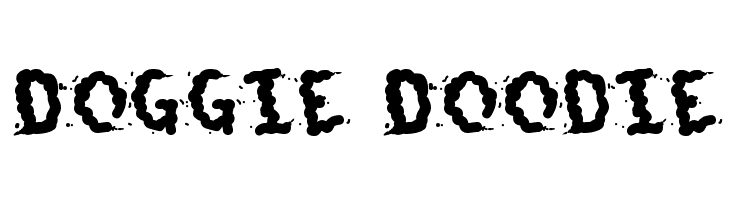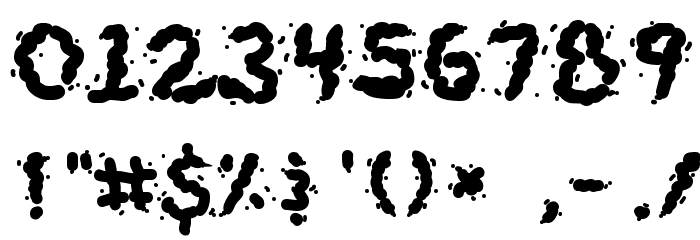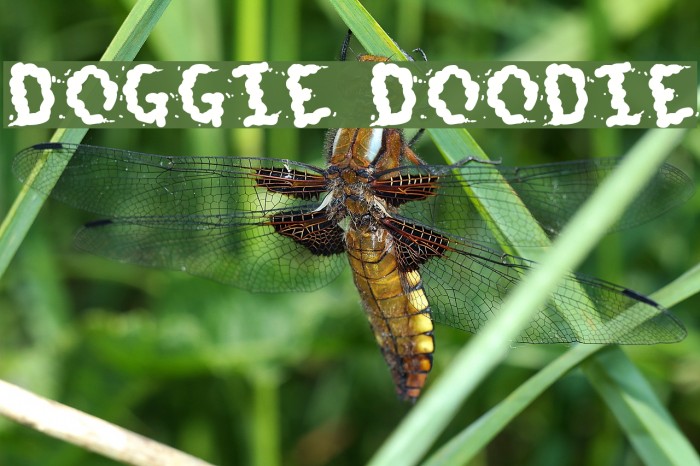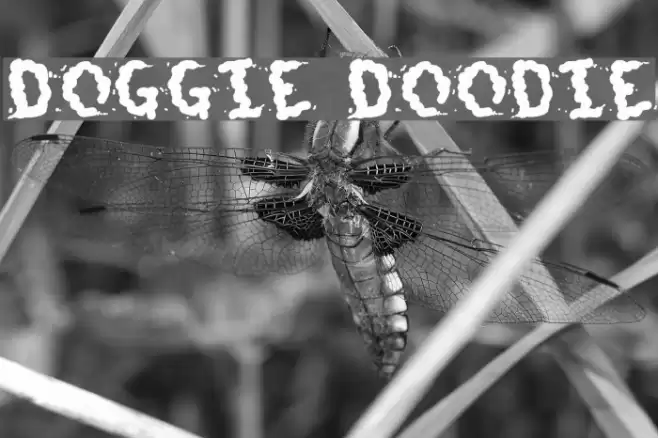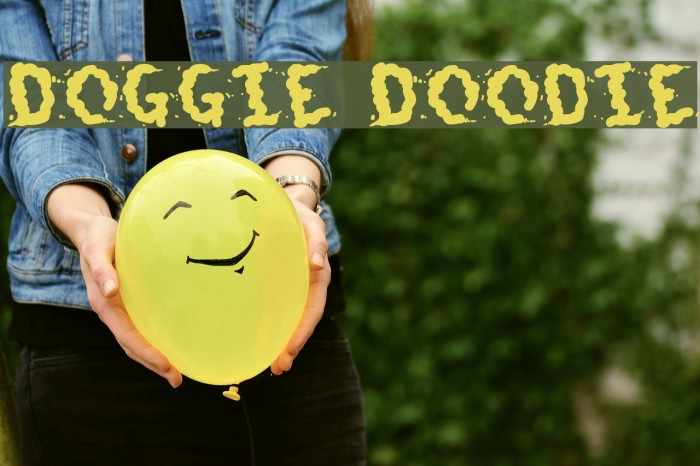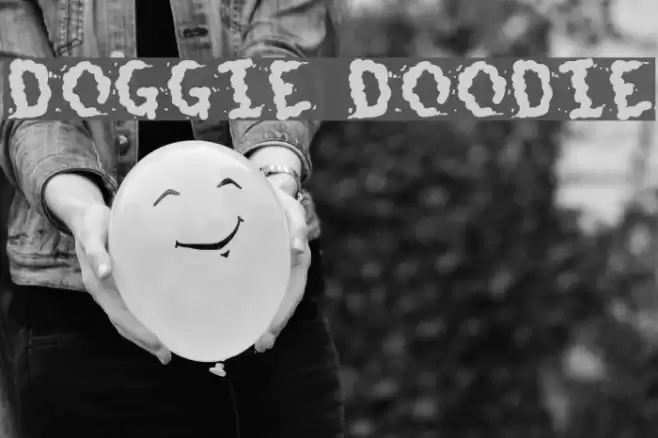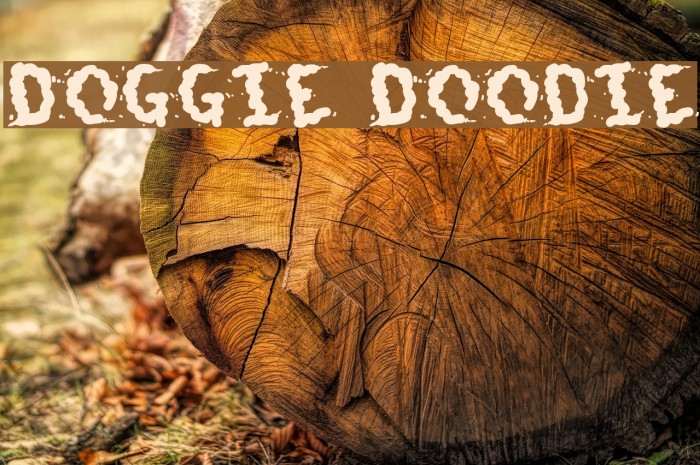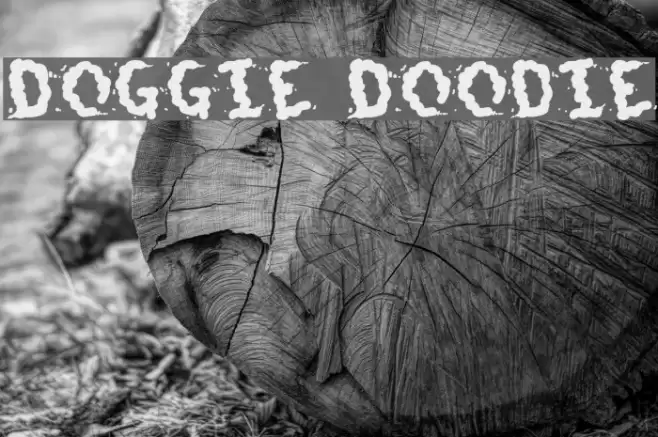
Doggie Doodie Font
| 分类 | Broken |
| 整体风格 | Playful, Artistic |
| 推荐项目 | Ideal for children's books, playful branding, artistic posters, and creative invitations. |